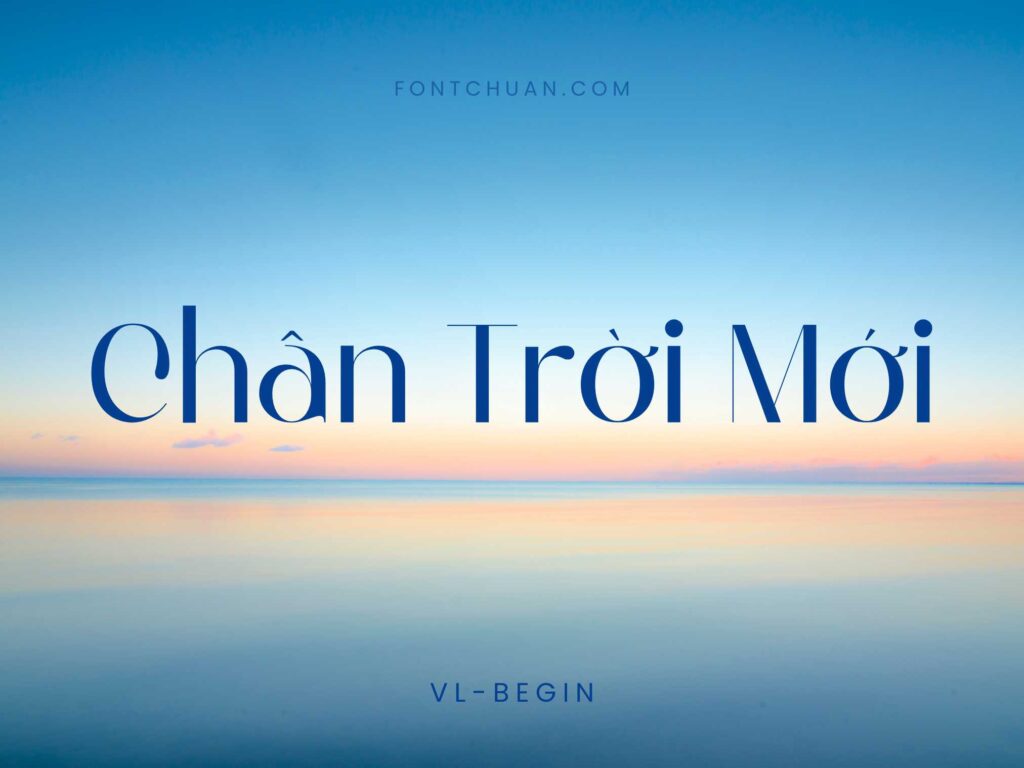
Font VL Begin Việt Hóa
VL-Begin là một phông chữ serif mang phong cách hiện đại và tinh tế, được thiết kế bởi Việt Linh. Phông chữ này có các đường nét thanh mảnh và uyển chuyển, tạo nên sự thanh lịch và chuyên nghiệp cho các thiết kế. VL-Begin hỗ trợ đầy đủ các ký tự tiếng Việt, giúp người dùng dễ dàng sử dụng trong các dự án sáng tạo. Phông chữ này được thành viên Font Chuẩn sưu tầm và đăng tải nhằm phục vụ nhu cầu thiết kế đa dạng.
Với thiết kế thanh lịch và rõ ràng, VL-Begin phù hợp cho các ứng dụng như tiêu đề, văn bản dài, thiết kế logo và các ấn phẩm in ấn. Trong lĩnh vực sự kiện, phông chữ này có thể được sử dụng trong các dịp như lễ cưới, hội nghị và các sự kiện văn hóa. Ngoài ra, VL-Begin cũng thích hợp cho các ngành nghề như thời trang, truyền thông và giáo dục.